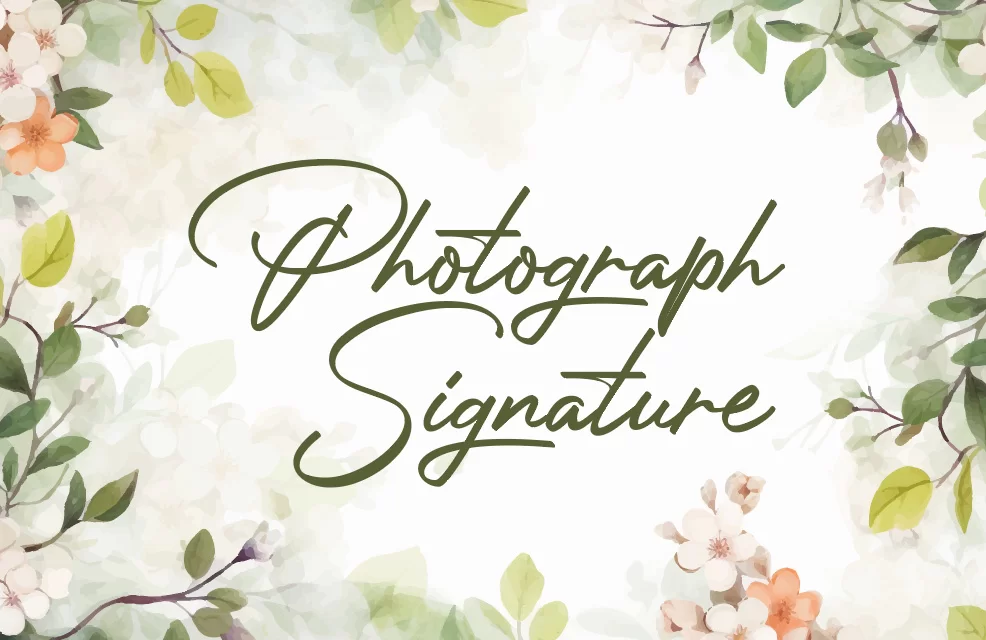
Phong cách bay bổng, tự nhiên như chữ ký viết tay. Font hỗ trợ đầy đủ dấu tiếng Việt, rất thích hợp cho các thiết kế mang tính cá nhân hóa.
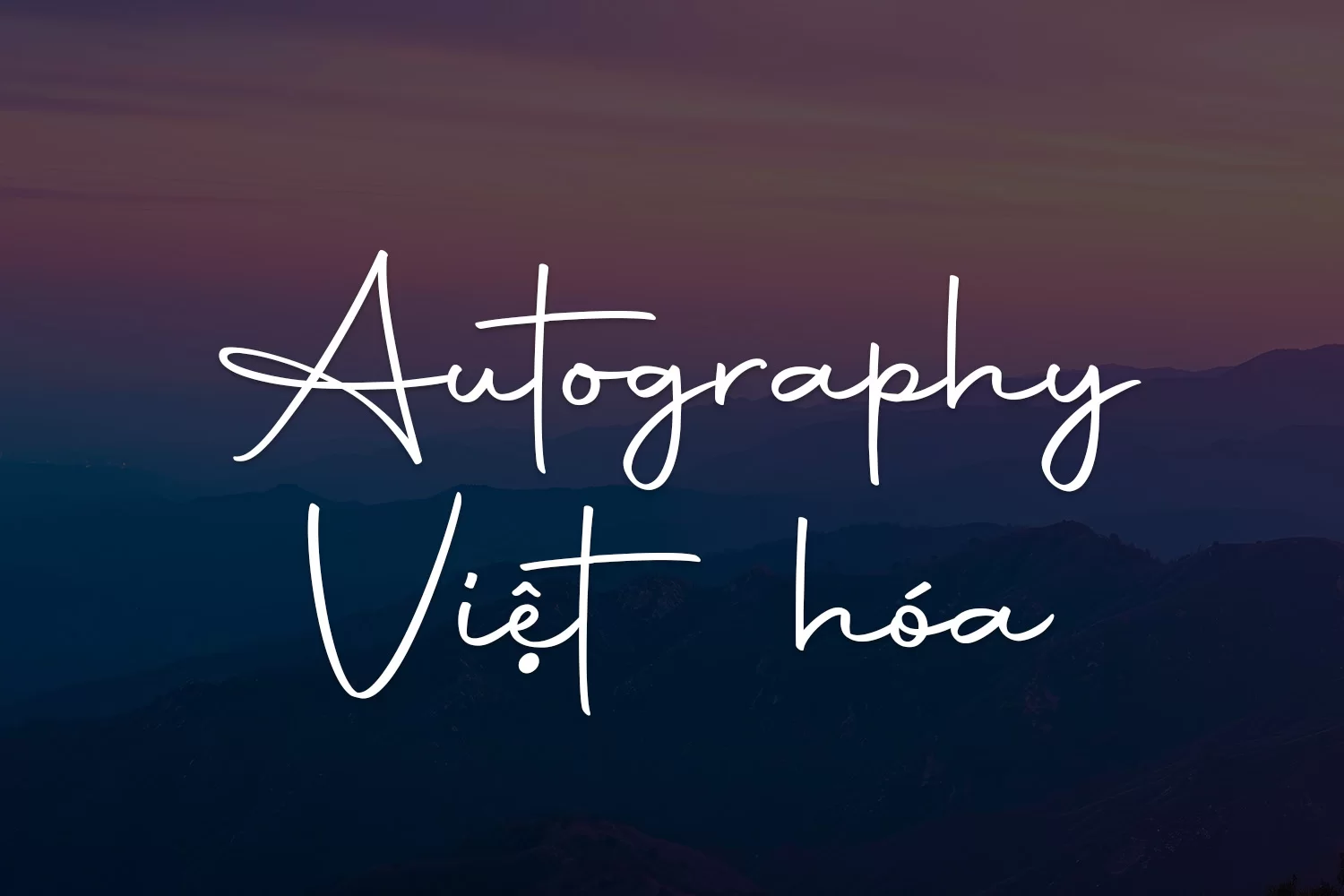
Vẻ ngoài thanh thoát, hơi hướng cổ điển, phù hợp với thiệp mời, bìa sách hoặc các thiết kế vintage.
Thiết kế mô phỏng chữ ký tay cực kỳ tự nhiên, mang đến sự chuyên nghiệp cho hồ sơ, hợp đồng hoặc logo cá nhân.
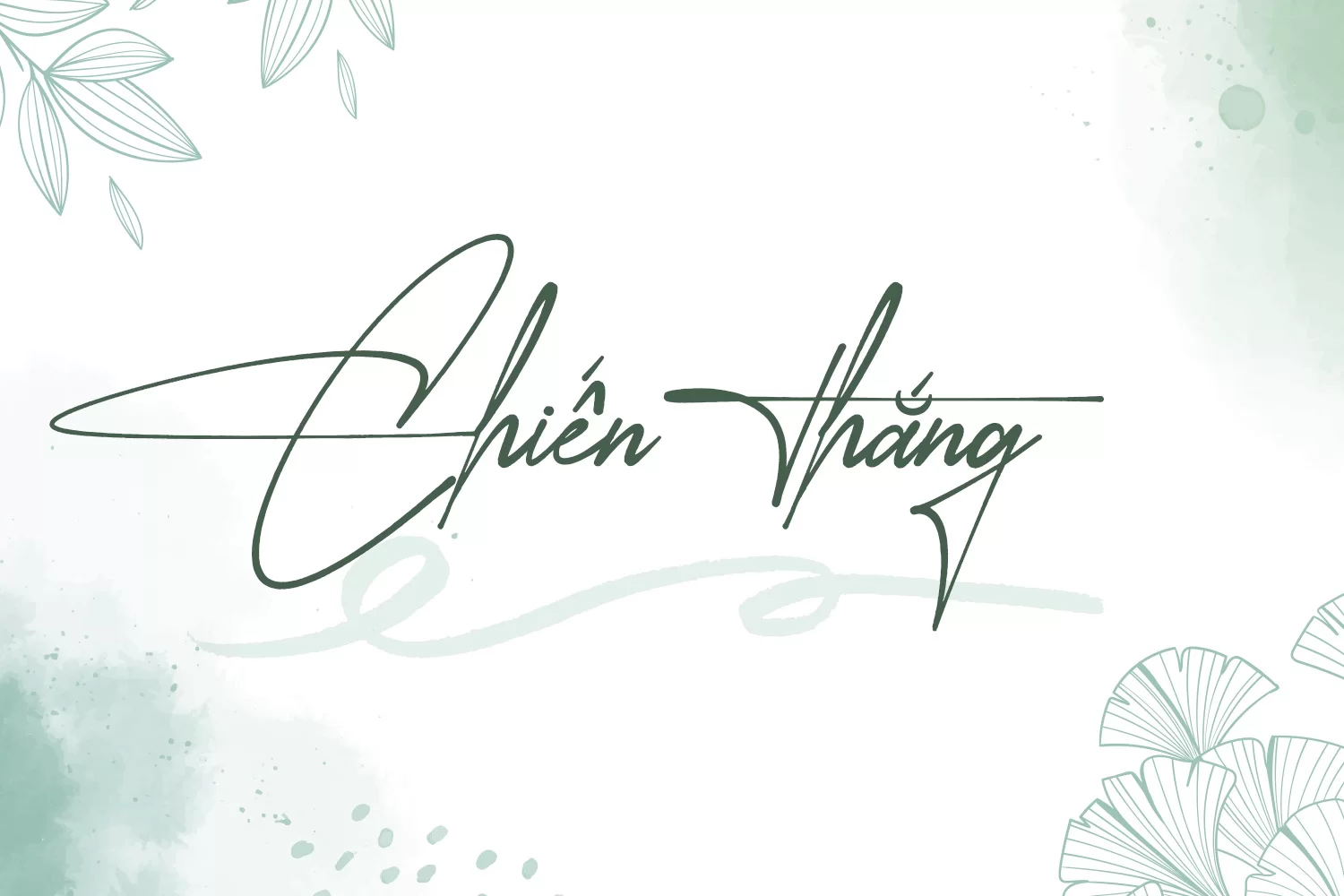
Font mang hơi hướng hiện đại, nam tính – thích hợp cho thương hiệu cá nhân hoặc sản phẩm công nghệ.
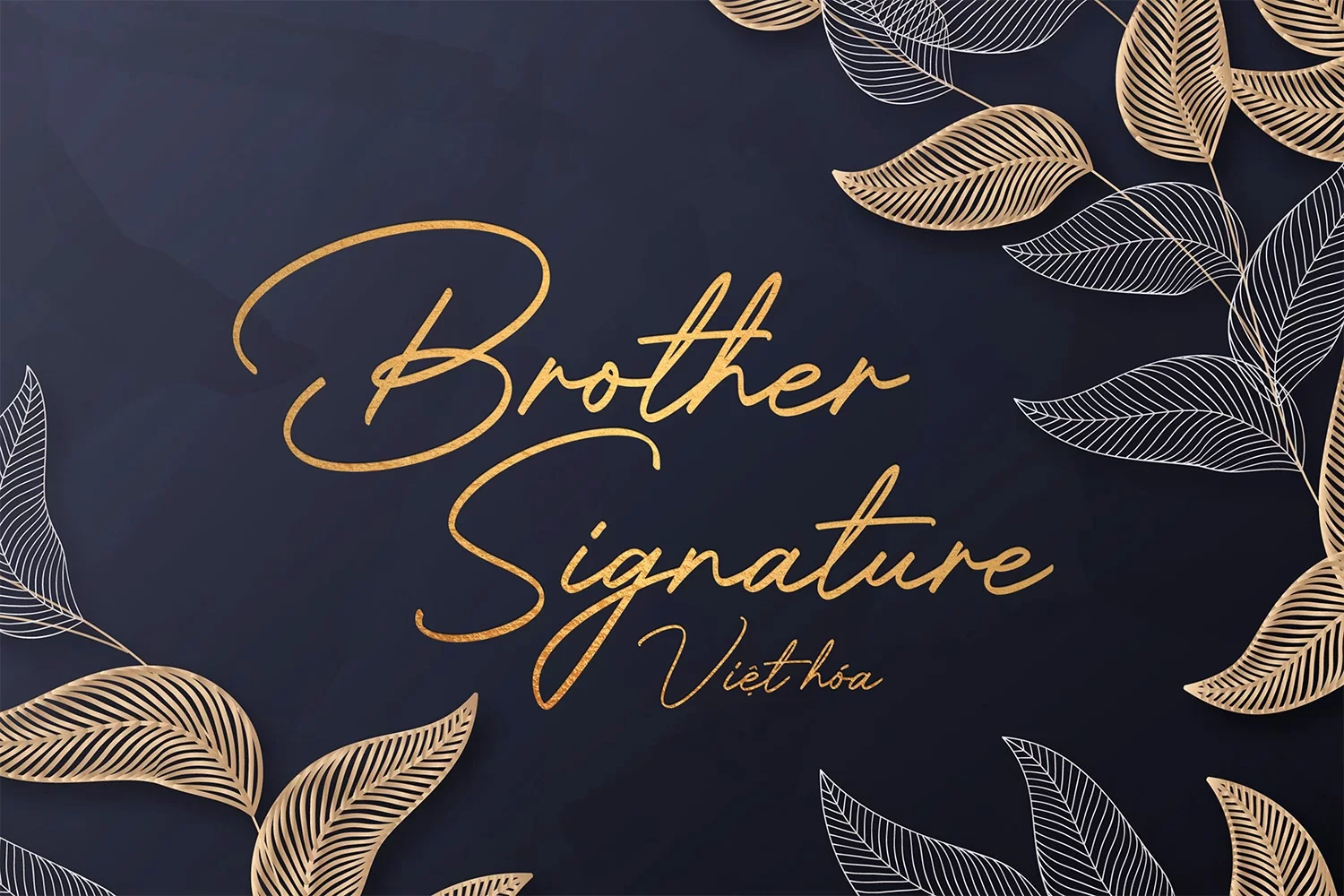
Đường nét mềm mại, thanh lịch, phù hợp với các thiết kế về mỹ phẩm, spa, thời trang cao cấp.
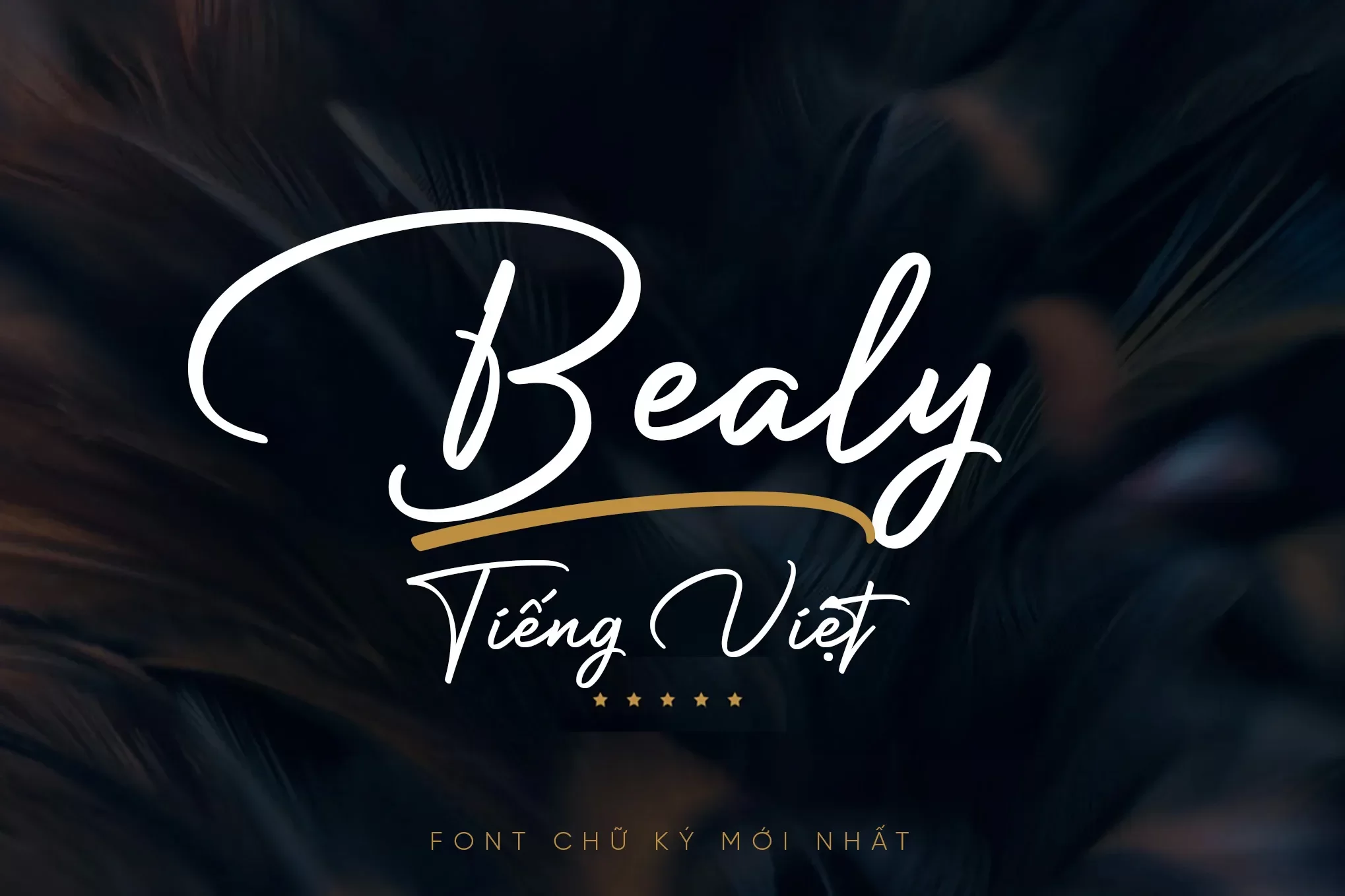
Font bay bổng, lãng mạn như thư tình – lý tưởng cho thiệp cưới, bài đăng social hoặc blog cá nhân.
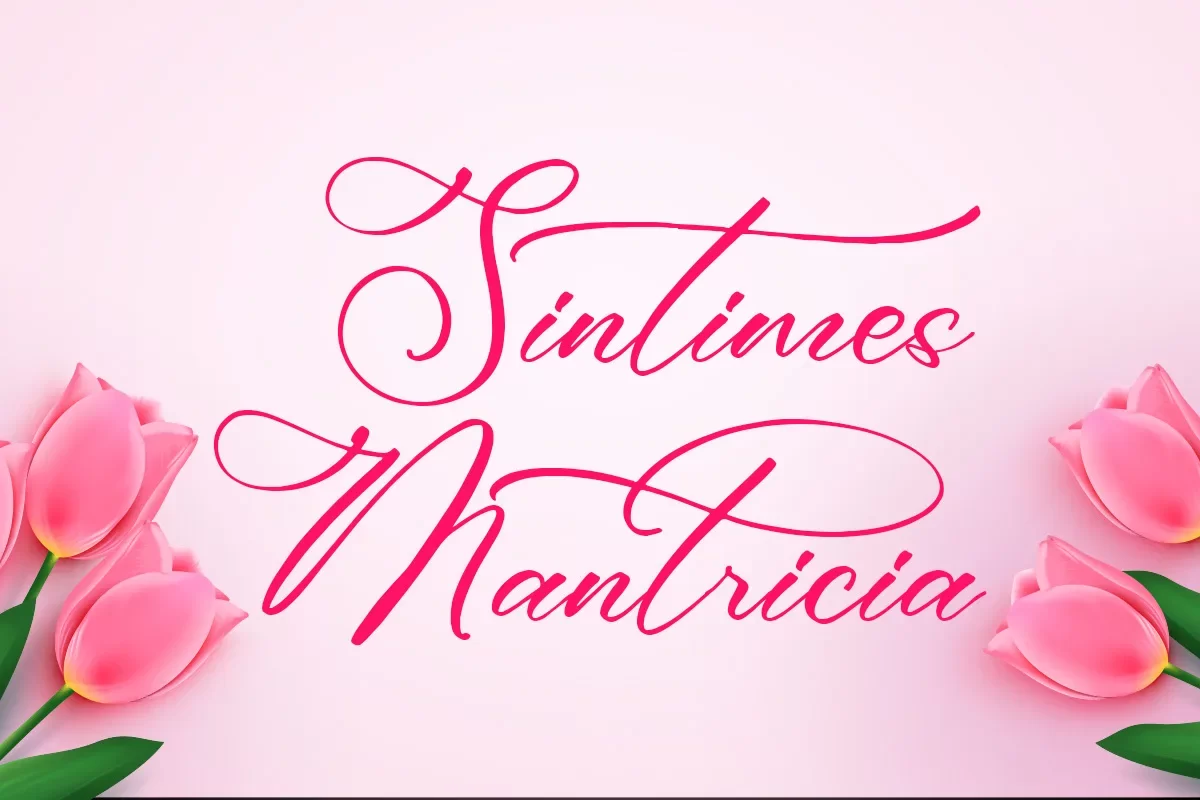
Font chữ viết tay rõ ràng, trang nhã – dành cho ai thích sự chỉn chu, lịch sự.
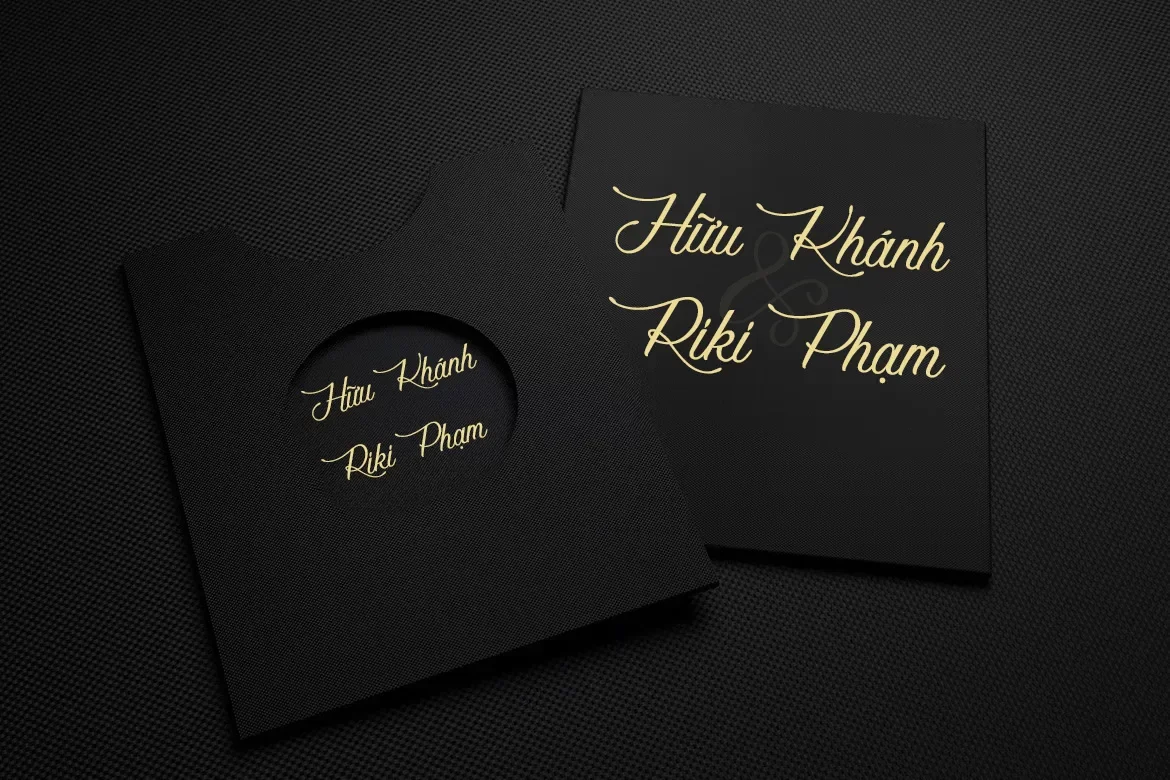
Font chữ ký mềm mại và có điểm nhấn. Thích hợp làm tiêu đề, chữ trang trí hoặc logo cá nhân nữ tính.
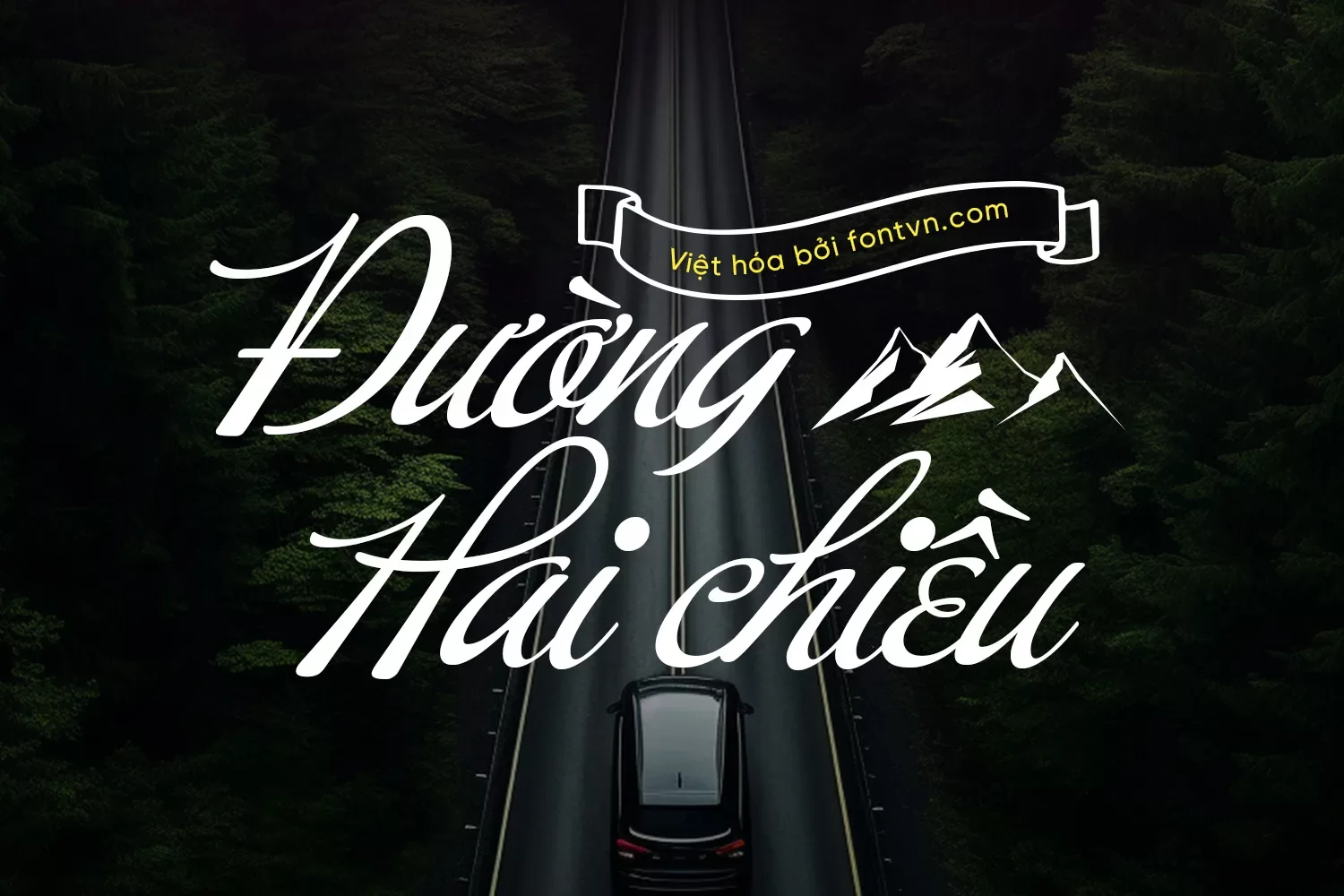
Font mang phong cách Paris cổ điển – kết hợp giữa sự thanh thoát và sang trọng.
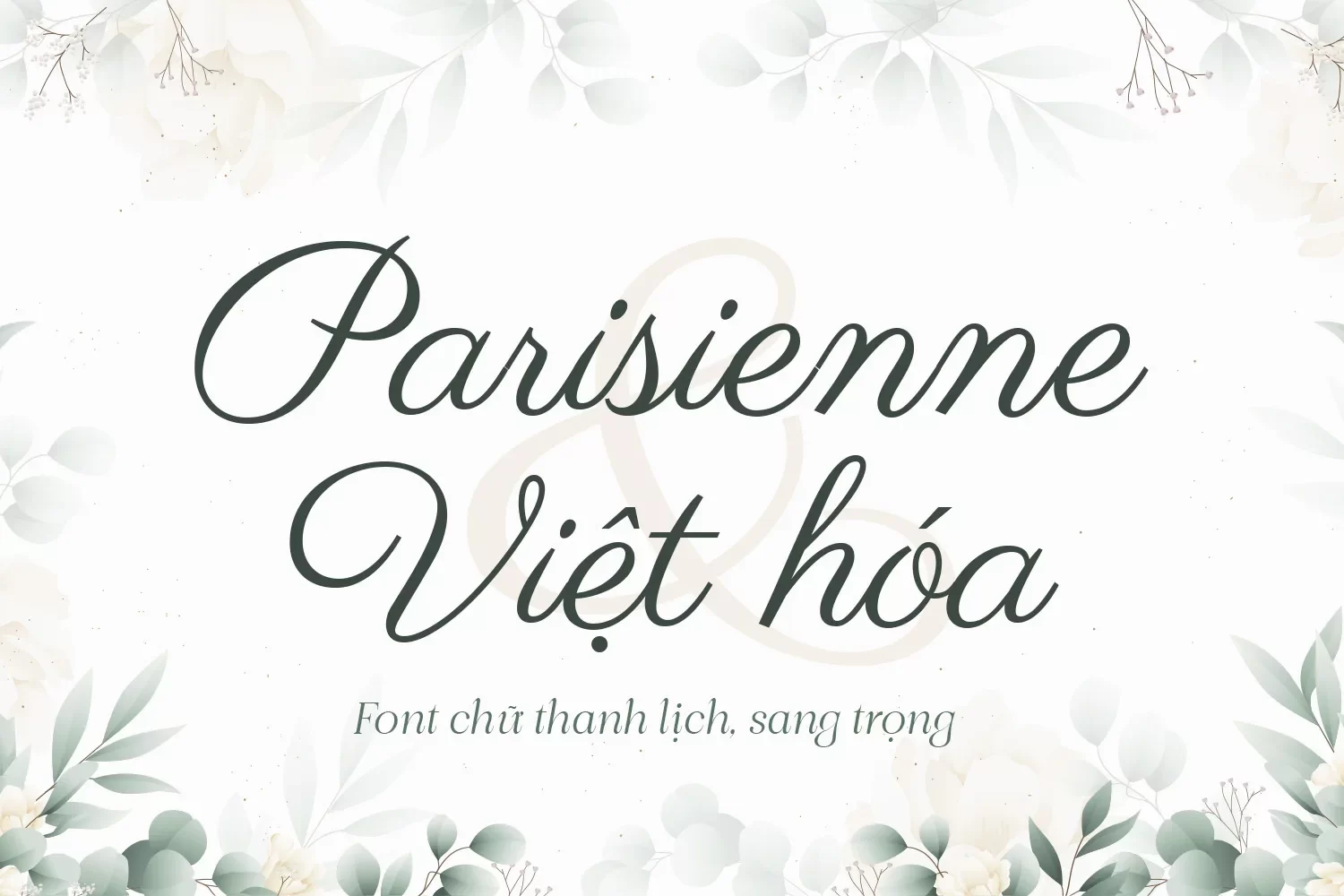
Font script đẹp mắt, có thể dùng để tạo hiệu ứng chữ ký trong poster, logo hoặc thiệp mời.
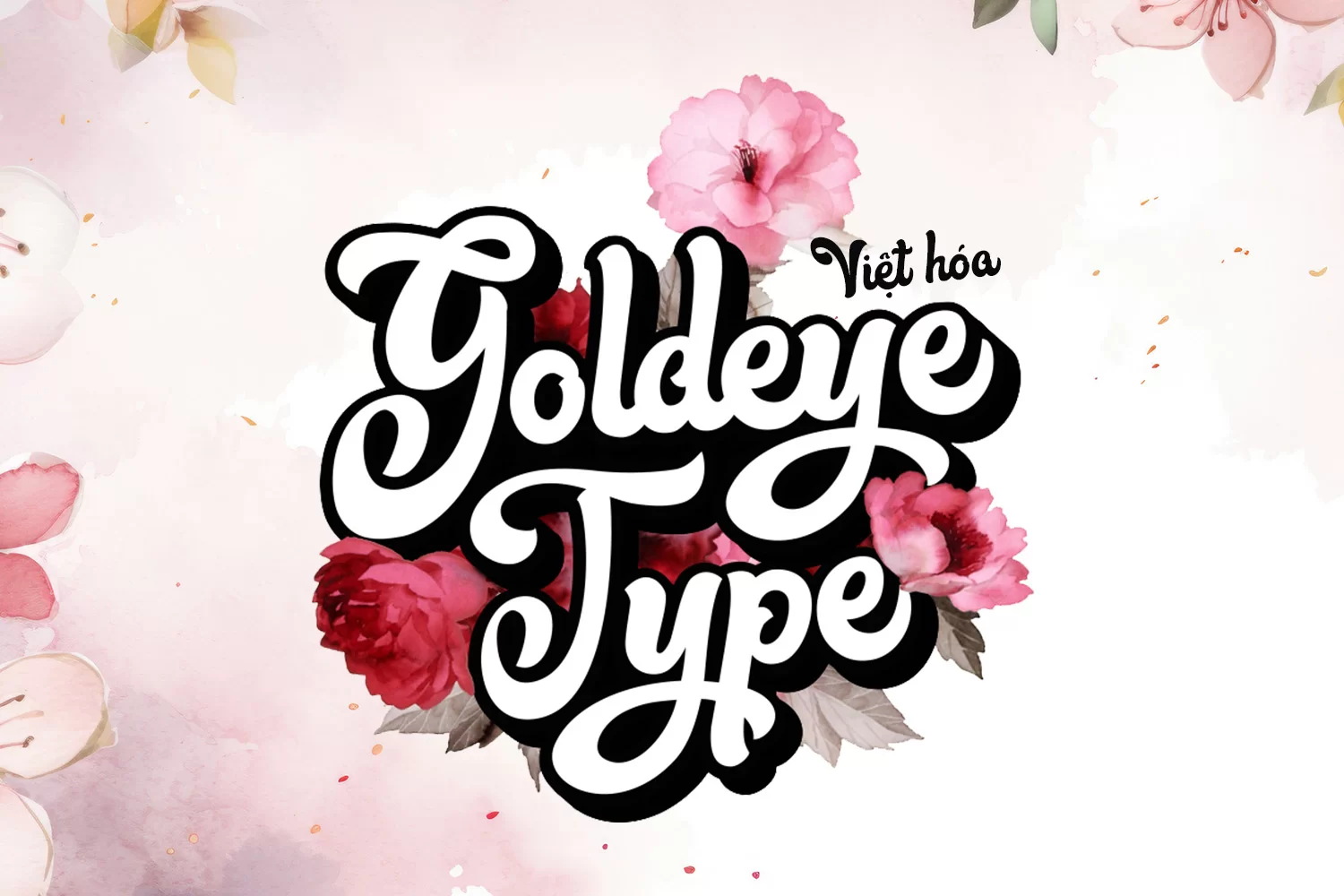
1. DVN Autography
Phong cách bay bổng, tự nhiên như chữ ký viết tay. Font hỗ trợ đầy đủ dấu tiếng Việt, rất thích hợp cho các thiết kế mang tính cá nhân hóa.
2. DVN Photograph Signature
Vẻ ngoài thanh thoát, hơi hướng cổ điển, phù hợp với thiệp mời, bìa sách hoặc các thiết kế vintage.
🖋 3. DVN Chữ Ký
Thiết kế mô phỏng chữ ký tay cực kỳ tự nhiên, mang đến sự chuyên nghiệp cho hồ sơ, hợp đồng hoặc logo cá nhân.
4. DVN Brother Signature
Font mang hơi hướng hiện đại, nam tính – thích hợp cho thương hiệu cá nhân hoặc sản phẩm công nghệ.
5. DVN Bealy
Đường nét mềm mại, thanh lịch, phù hợp với các thiết kế về mỹ phẩm, spa, thời trang cao cấp.
6. Sinetimes Mantricia
Font bay bổng, lãng mạn như thư tình – lý tưởng cho thiệp cưới, bài đăng social hoặc blog cá nhân.
7. DVN Scriptorial
Font chữ viết tay rõ ràng, trang nhã – dành cho ai thích sự chỉn chu, lịch sự.
8. DVN Buffet Script
Font chữ ký mềm mại và có điểm nhấn. Thích hợp làm tiêu đề, chữ trang trí hoặc logo cá nhân nữ tính.
9. DVN Parisienne
Font mang phong cách Paris cổ điển – kết hợp giữa sự thanh thoát và sang trọng.
🖌 10. Goldeye Type
Font script đẹp mắt, có thể dùng để tạo hiệu ứng chữ ký trong poster, logo hoặc thiệp mời.